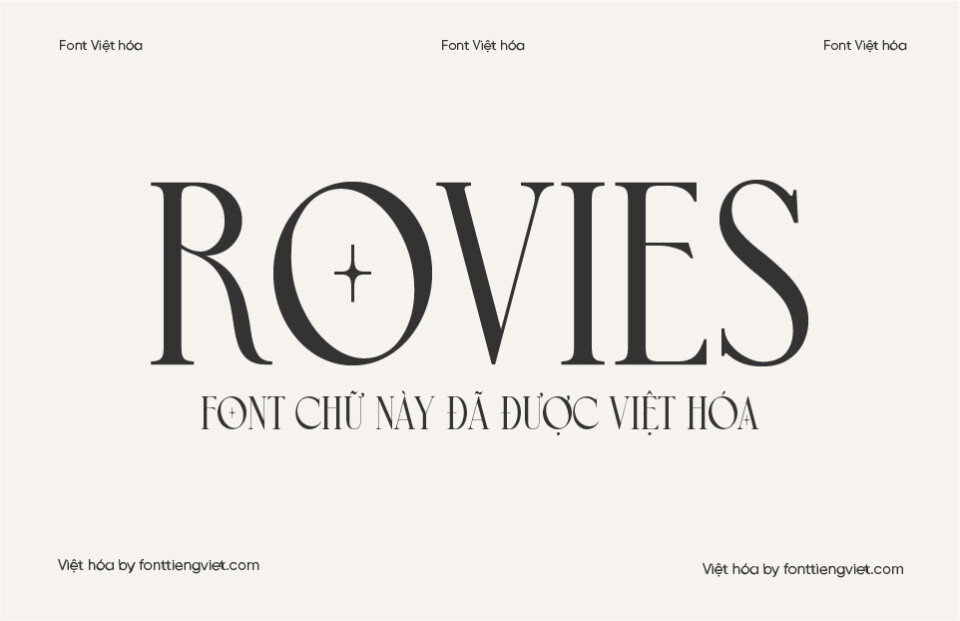
Font Việt hóa 1FTV VIP Rovies
Font Việt hóa 1FTV VIP Rovies – Lựa chọn hoàn hảo cho thiết kế hiện đại
Giới thiệu về Font Việt hóa 1FTV VIP Rovies trong thiết kế đồ họa
Trong thế giới sáng tạo ngày nay, việc lựa chọn một bộ Font Miễn Phí chất lượng luôn là ưu tiên hàng đầu của các nhà thiết kế chuyên nghiệp lẫn các bạn học sinh sinh viên. Một trong những cái tên đang thu hút sự chú ý lớn chính là Font Việt hóa 1FTV VIP Rovies. Đây là một bộ font mang phong cách hiện đại, thanh lịch nhưng không kém phần mạnh mẽ, rất phù hợp cho các dự án đòi hỏi sự tinh tế và tính thẩm mỹ cao. Việc sử dụng Font Việt hóa 1FTV VIP Rovies giúp người dùng giải quyết triệt để vấn đề lỗi font khi gõ tiếng Việt, mang lại trải nghiệm làm việc mượt mà trên nhiều nền tảng phần mềm khác nhau từ Office đến Adobe.
Đặc điểm nổi bật của bộ Font Việt hóa 1FTV VIP Rovies
Cấu trúc đường nét tinh tế và đa dạng
Bộ Font Việt hóa 1FTV VIP Rovies được đánh giá cao nhờ cấu trúc các chữ cái được chăm chút tỉ mỉ. Với các đường nét rõ ràng, độ dày vừa phải, bộ font này tạo nên một tổng thể hài hòa và dễ nhìn. Đặc biệt, các ký tự dấu tiếng Việt đã được tối chỉnh sao cho không bị lệch hay chồng chéo lên các chữ cái chính. Điều này cực kỳ quan trọng đối với các bạn học sinh khi làm bài thuyết trình hoặc giáo viên soạn thảo giáo án điện tử, giúp văn bản trở nên chuyên nghiệp và dễ đọc hơn bao giờ hết.
Tính ứng dụng linh hoạt trong nhiều lĩnh vực
Không chỉ giới hạn trong việc soạn thảo văn bản thông thường, Font Việt hóa 1FTV VIP Rovies còn tỏa sáng trong lĩnh vực thiết kế thương hiệu và truyền thông. Bạn có thể sử dụng bộ font này để làm tiêu đề bài viết, thiết kế banner quảng cáo, hay thậm chí là trình bày các báo cáo dự án học đường. Sự linh hoạt giữa các biến thể đậm, nhạt của font giúp người dùng dễ dàng tạo ra sự phân cấp thông tin rõ ràng, giúp người xem nắm bắt nội dung nhanh chóng và hiệu quả.
Lợi ích khi sử dụng Font Việt hóa 1FTV VIP Rovies cho người dùng Việt
Tương thích tốt với các bộ gõ tiếng Việt phổ biến
Tiết kiệm thời gian và nâng cao tính chuyên nghiệp
Thay vì tốn hàng giờ đồng hồ để tìm kiếm và chỉnh sửa lỗi hiển thị, việc lựa chọn Font Việt hóa 1FTV VIP Rovies ngay từ đầu sẽ giúp bạn tiết kiệm được rất nhiều thời gian quý báu. Với các đường nét mang hơi thở của thời đại mới, bộ font này giúp mọi tác phẩm từ đơn giản đến phức tạp đều mang một vẻ ngoài chuyên nghiệp và đẳng cấp. Đối với môi trường giáo dục, điều này giúp các em học sinh rèn luyện tư duy thẩm mỹ và sự chỉnh chu trong từng bài làm, từ đó đạt được những kết quả học tập tốt hơn trong các môn học liên quan đến công nghệ và nghệ thuật.
Kết luận về bộ Font Việt hóa 1FTV VIP Rovies